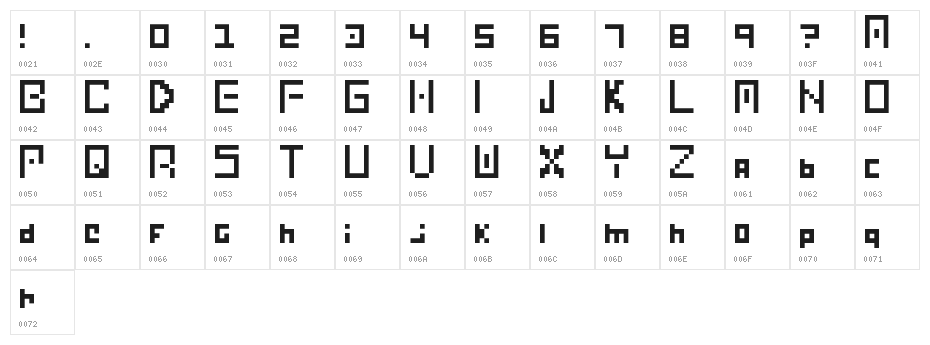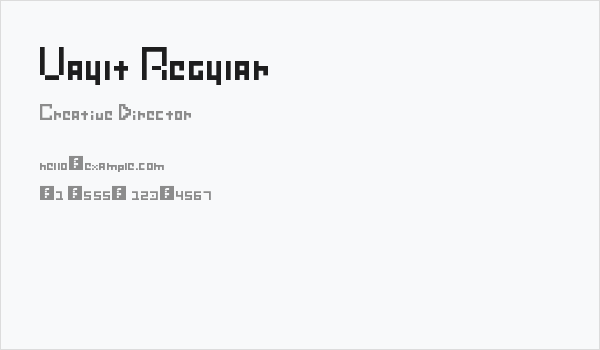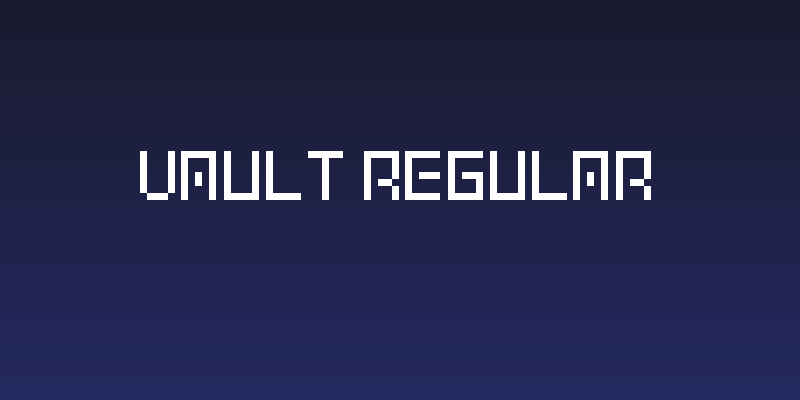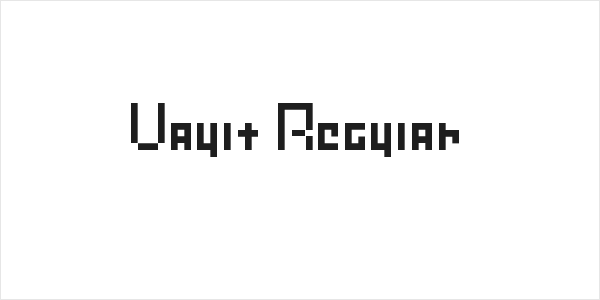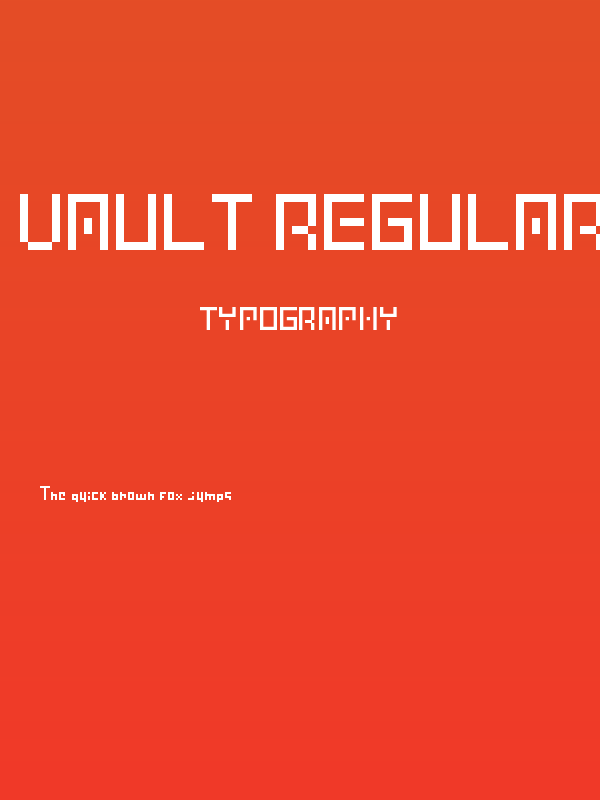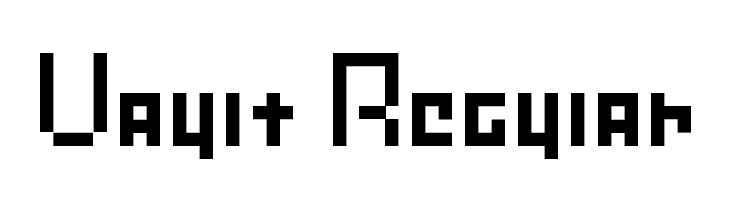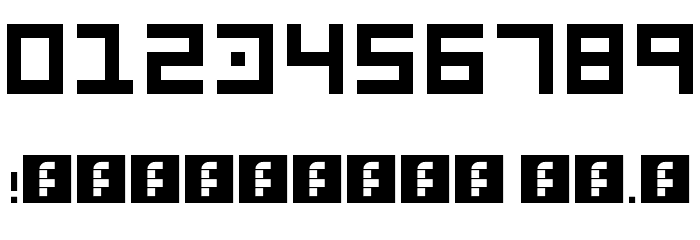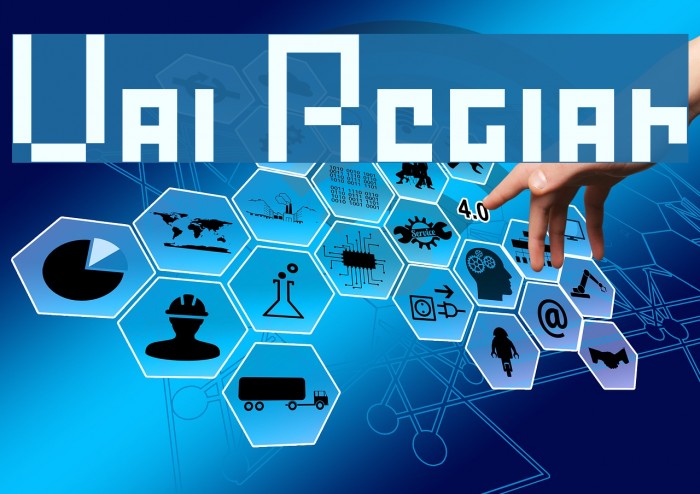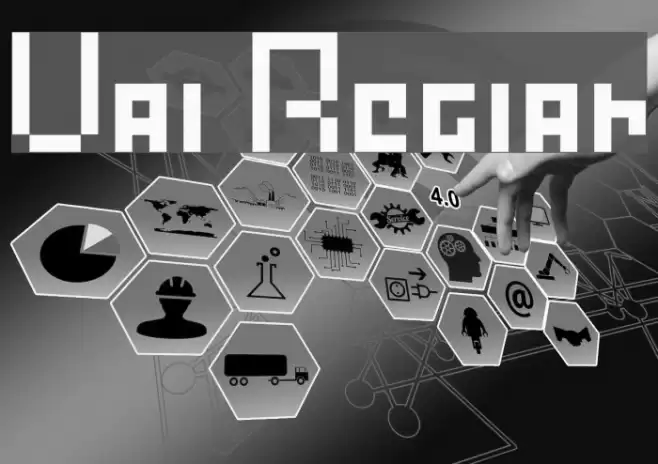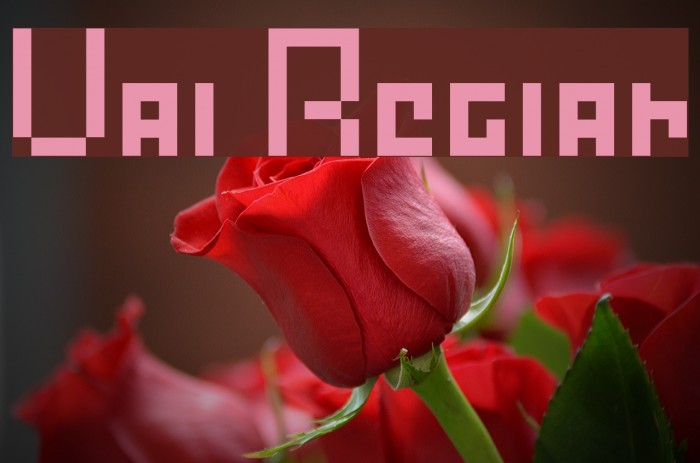
Vault Regular Font
| Stil general | Modern, Retro, Digital |
| Caz de utilizare | Headlines, Logos, Posters, Digital Art |
| Proiecte propuse | Ideal for video game design, tech branding, digital art projects, or any creative work that seeks a retro or futuristic vibe. |